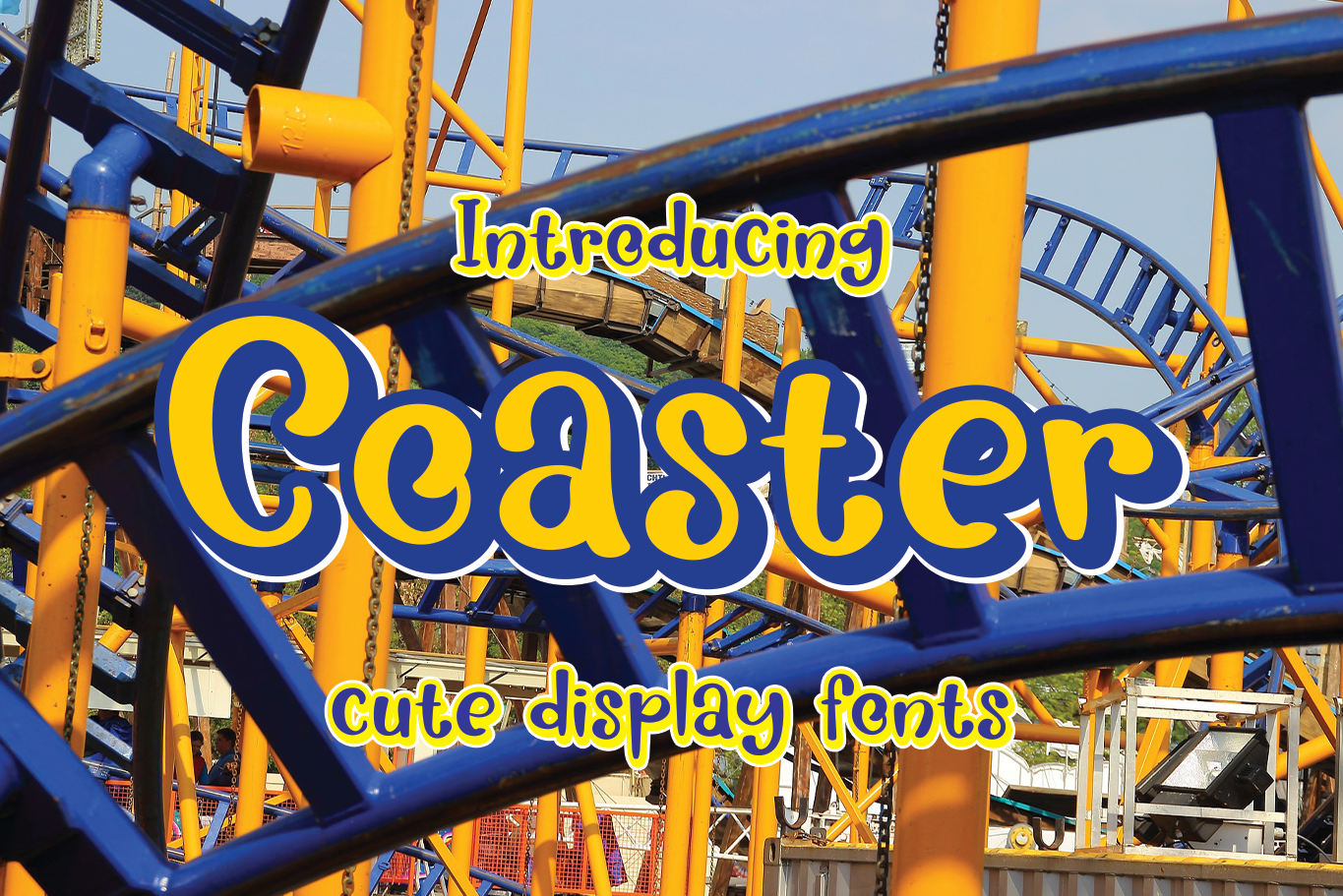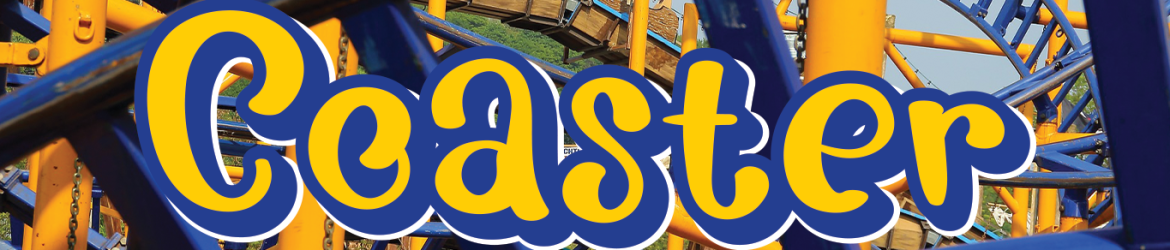
A fonte Coasters é perfeita para quem busca uma maneira criativa de decorar seus logotipos e identidades visuais, seja para projetos de branding ou até mesmo ideias DIY no Instagram ou em redes sociais pessoais. Desenvolvida pelo Erik Studio, essa font apresenta um estilo clean que também traz elementos ligeiramente descontraídos e divertidos, criando uma pegada única e atraente. Com seu design elegante e personalizado, Coasters é perfeitamente adaptável para múltiplos usos em diversas plataformas digitais. Ideal tanto para expressar sua marca de maneira moderna e sofisticada quanto para dar um toque criativo nas suas redes sociais ou no design DIY que você está planejando. Seja ela a fonte escolhida para as letras na sua página da rede social, o nome em um kit de pintura de parede, ou até mesmo como o título do seu próximo projeto artístico – Coasters certamente trará uma dose extra de criatividade e personalização para esses projetos.